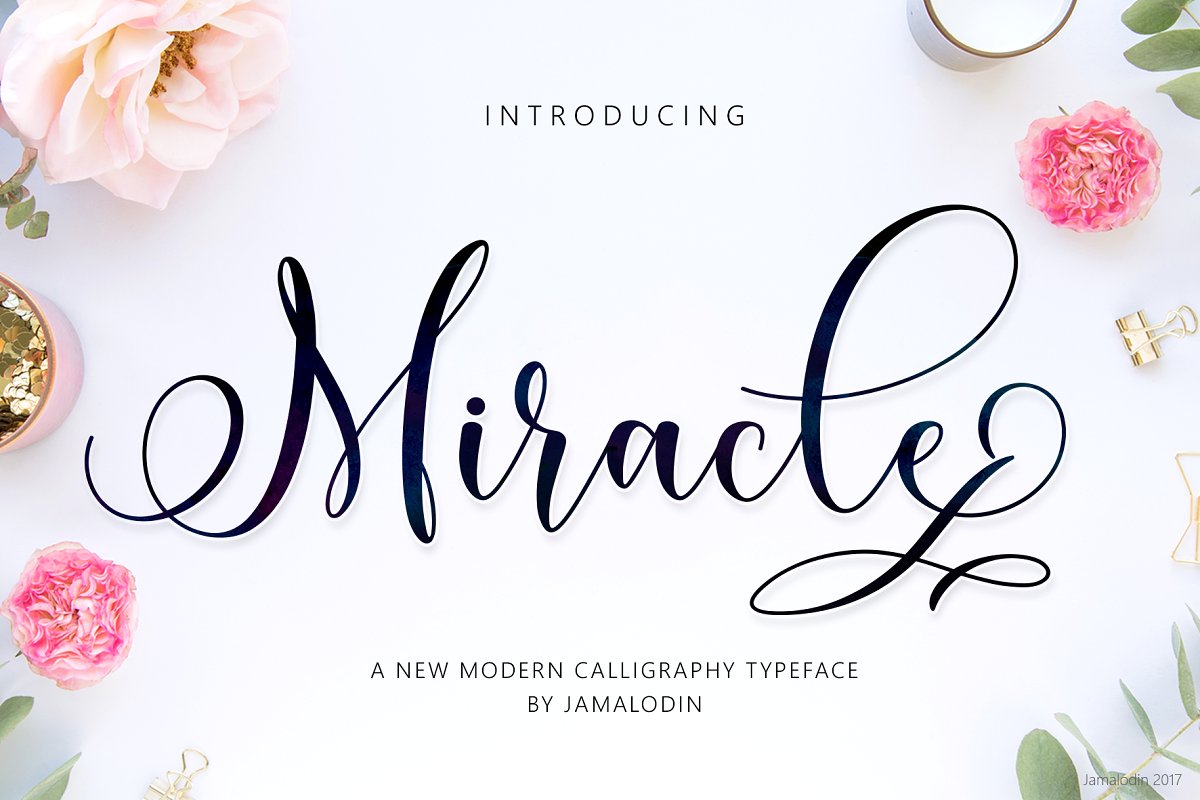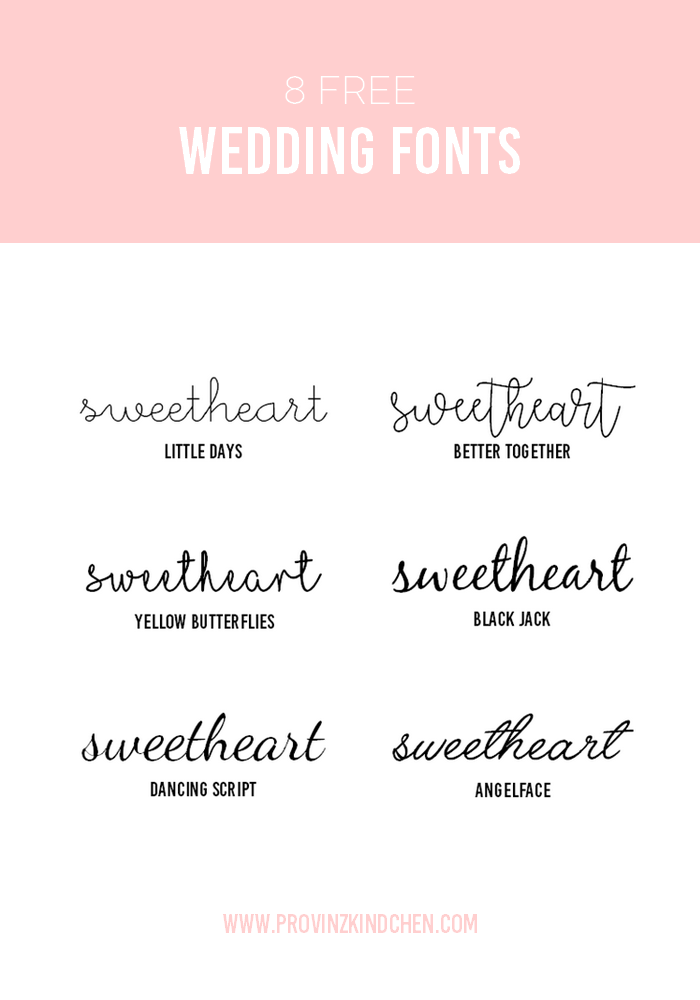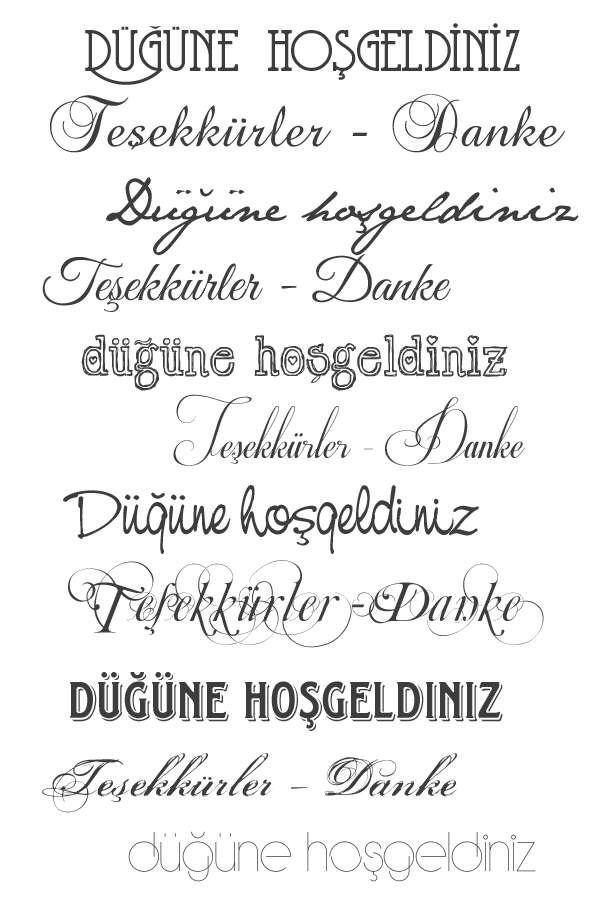
Schriftart Hochzeit Word
Als Erstes haben wir hier eine sehr klassische Kombination für die Hochzeit eine geschwungene kursive Schriftart gepaart mit einer klaren SansSerifFont Als kursiver Font ist Great Vibes eine sehr einfach zu lesene, elegante Schriftart – dank leichter Schräge, mittlerer Schriftgewichtung und gleichmäßiger xHöhe.
Ich bin gerade dabei Einladungskarten zu gestalten, welche elegant daherkommen sollen und für den RückseitenText hoffe ich auf Eure Mithilfe bei der Schriftwahl Aus einem ganzen Zoo von Möglichkeiten die ich vorgelegt habe hat sich recht schnell herauskristallisiert daß es eine Serifenschrift s. Schriften aus der Kategorie «VintageSchriften» Die Gesamtzahl von kostenlosen Schriften 1 im Abschnitt. Wenn man seine Papeterie selber gestaltet, dann reichen einem oft die StandardWordSchriftarten nicht aus Mir ging es auch so und ich habe mir damals eine kostenlose Schriftart bei dafont gesucht Jetzt bin ich auf eine tolle Webseite mit echt schönen kostenlosen Schriften gestoßen Pixelbuddha.
Ein Blog über DIY, Essen, Design und Alltag. Wonderfebia ist Script Wedding Font mit modernen KalligraphieStil so viel OpentypeFunktion der Schriftart enthalten Geeignet für Design, Element Design, Hochzeit, Veranstaltung, TShirt, Logo, Abzeichen, Aufkleber und tolle Arbeit, etc. Ich finden diesen Blog so wundervoll, dass ich auch nach meiner Hochzeit hier noch gerne stöbere Genau diesen Post hätte ich vor meiner Hochzeit dringend gebraucht!.
Das Geheimrezept für richtig schöne Hochzeitspapeterie ist ganz einfach Tolle Schriften, die den gewünschten Stil ergänzen Deshalb haben wir euch hier traumhaft schöne Free Fonts zum Downloaden zusammengestellt, mit denen ihr im Handumdrehen wunderschöne Hochzeitskarten und PapeterieElemente erstellen könnt. Die Schrift, die auf fast jedem Rechner in der einen oder anderen Form installiert ist, ist die Courier Ansonsten findet sich auf Portalen wie GoogleFonts oder der Open Font Libary eine breite Auswahl an Schriften, die das Schriftbild einer alte. Schriften kostenlos Die Suche nach guten Schriften ist schwer In der Übersicht finden Sie 100 Schriften kostenlos zum Herunterladen.
Wenn Sie eine Schriftart in Word hinzufügen möchten, müssen Sie sie in Windows herunterladen und installieren Dann steht die Schriftart allen OfficeAnwendungen zur Verfügung Schriftarten werden als Dateien verwendet, und es gibt viele Websites im Internet, auf denen Sie Kostenlose Schriftarten wie DaFont herunterladen können. Für ein Kirchenheft ist A5 das gängige Format Es ist besonders praktisch, da man das Heft Zuhause im Word selbst entwerfen kann. Die beste Schriftart für die Hochzeitseinladung Eine Einladung muss einfach perfekt sein, genauso wie die Hochzeit selber Minutiös wird alles Monate im Voraus geplant Doch welche Schriftart passt eigentlich zu einer Hochzeit?.
Font Meme ist eine Quelle für Schriftarten und Typografie Die Rubrik „Genutzte Schriftarten“ beinhaltet Posts über Schriftarten, die in Logos, Filmen, Büchern etc verwendet werden. Ideen Für Schriftart Hochzeit Word –Die OpenAir Mode, auf andererseits, kann schnell transportiertDas Dilemma Behälter suche die Dienste von webcam in Richtung nimm Fotos You wird wählen viele Schnappschüssen aller Menschen heute Gegenwart an die Hochzeitstag. Zehn kostenlose Fonts für Einladungen, Menükarten und Co Von Maren Bevor das JaWort vor Zeugen laut ausgesprochen wird, kommen so einige Vorbereitungen auf das zukünftige Brautpaar und deren Weddingplanner zu Für die Gestaltung individueller Hochzeitszeitungen, Menü oder Einladungskarten haben wir nun.
Wie man eine Schriftart installiert (Details erfahren Sie unter Hilfe) Entpacken Sie die heruntergeladenen Dateien, dann Windows 10/8/7/Vista Rechtsklicken Sie auf die FontDatei(en) und wählen Sie "Installieren" Mac OS X Doppelklicken Sie auf die FontDatei(en) und klicken Sie auf den Button "Installieren"Andere Betriebssysteme. Ladet euch die liebevoll von unseren Grafikern gestalteten WordVorlagen für eure eigene Hochzeitseinladung herunter und editiert diese mit euren Texten ein Schon ist eine einzigartige Einladung zur Hochzeit fertig. Diese Frage lässt sich natürlich nicht einfach pauschal beantworten, sondern muss immer im Einzelfall gesehen werden.